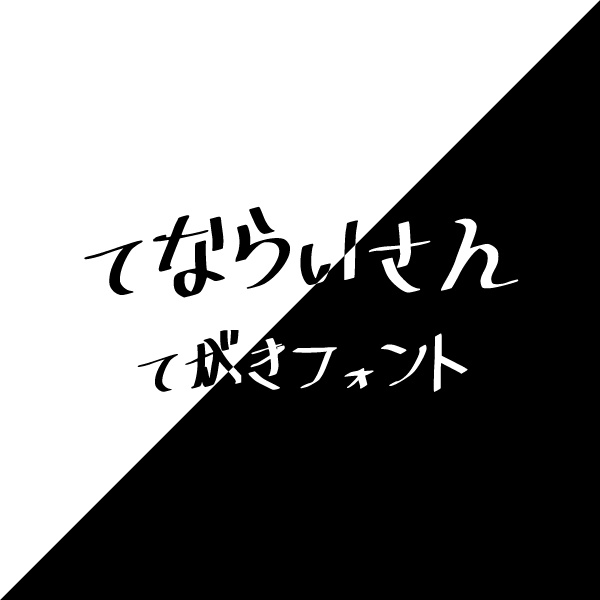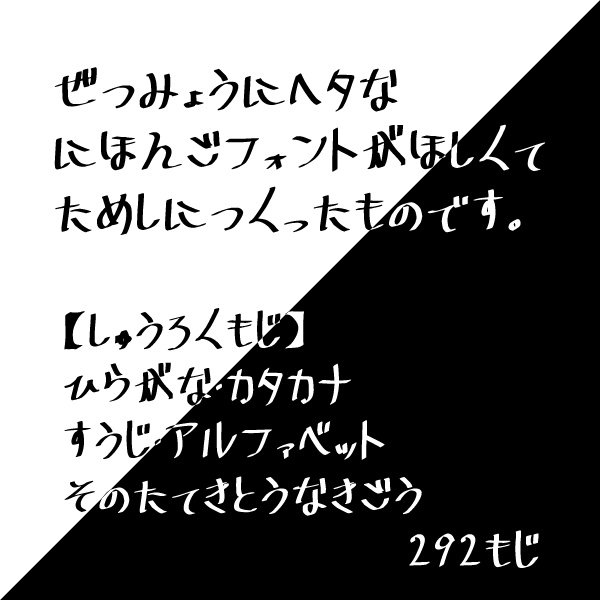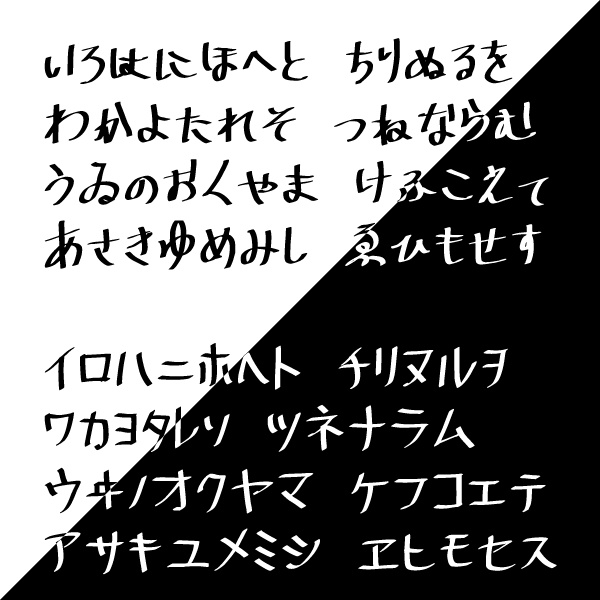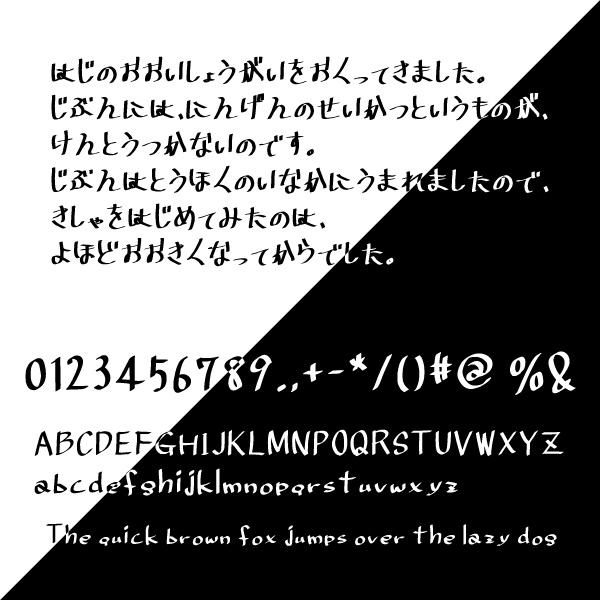
【無料】手書き風フォント「てならいさん」
「てならいさん」は、絶妙にヘタな手書き文章が打てるフォントが欲しくて試しに作ってみたフォントです。 少しバランスが悪い手書き風の文章を書くのに適しています。 【収録文字】全292文字 ・全角ひらがな、カタカナ ・半角アルファベット(大文字/小文字) ・半角英数字 ・記号類 【利用規約】 ・商用/非商用問わず利用可能(同人作品含)。 ・フォントデータの改変・無断転載・再配布・販売禁止。 ・当フォントを利用した制作物、ロゴなどの商標登録禁止。 (当フォントを使用してのロゴマーク作成は問題ありません) 当フォントを利用して発生した、いかなる損害についても作者は責任を負いません。 ※予告なしにバージョンアップを行うことがあります。 ※一部の端末、ソフトウェアでは使用できない場合がございます。